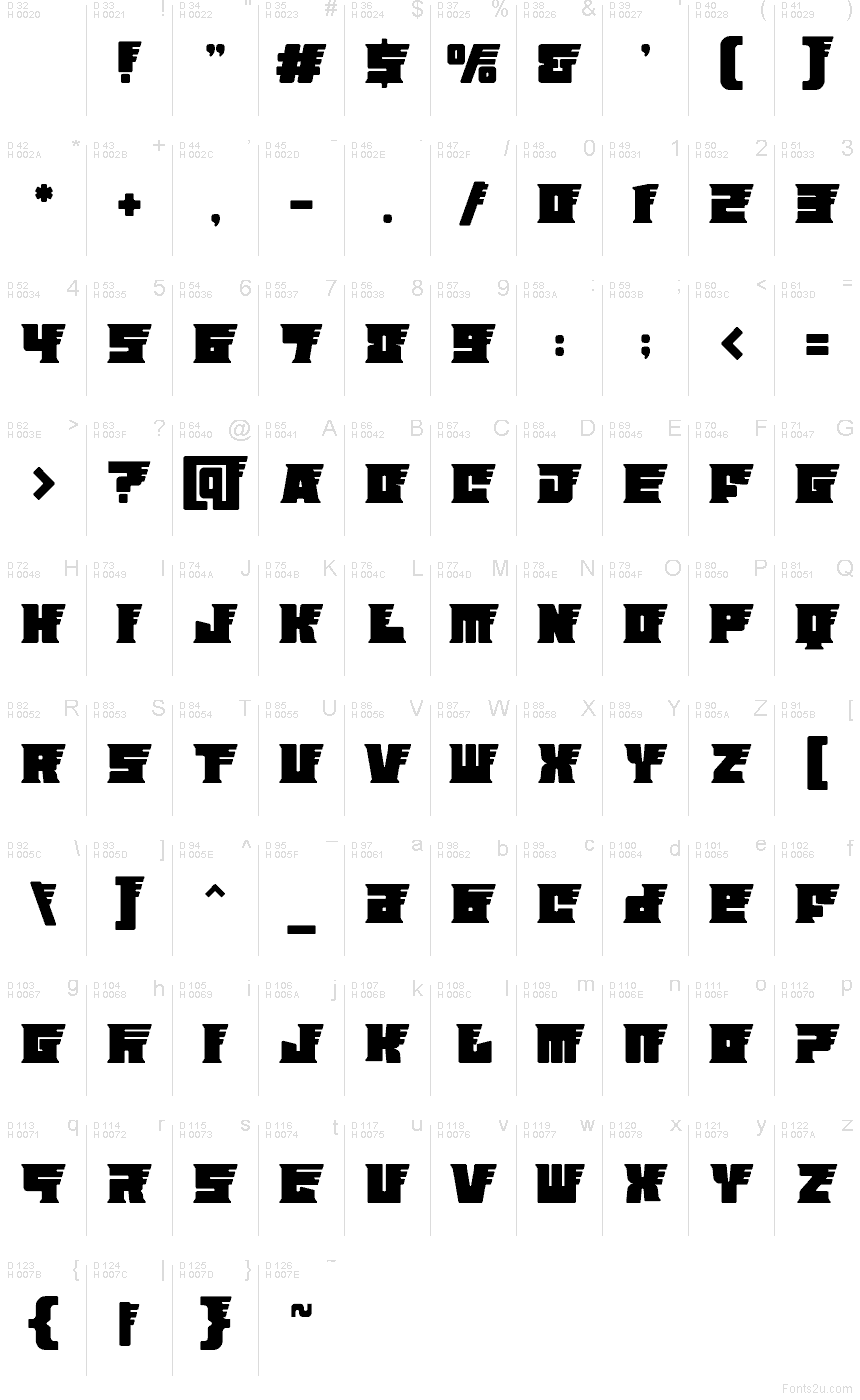
Astral Zenith Twelve od Putracetol Studio je bezplatné sci-fi display písmo, které definují široké, blokové tvary a opakující se horizontální řezy, jež protínají písmena jako ukazatele signálu. Tato stupňovitá přerušení dodávají designu řízný elektronický rytmus, takže znaky působí spíše mechanicky a jako kód než jen jako dekorace.
Skvěle se uplatní v názvech her, na plakátech, přebalech alb, letácích nebo grafikách pro streamery, kde pevná futuristická textura dokáže víc než běžné písmo. Krátké brandingové texty a loga také těží z těchto vrstvených a segmentovaných tvarů, které vytvářejí silnou grafickou hmotu ještě před přidáním barev nebo efektů.
Astral Zenith Twelve